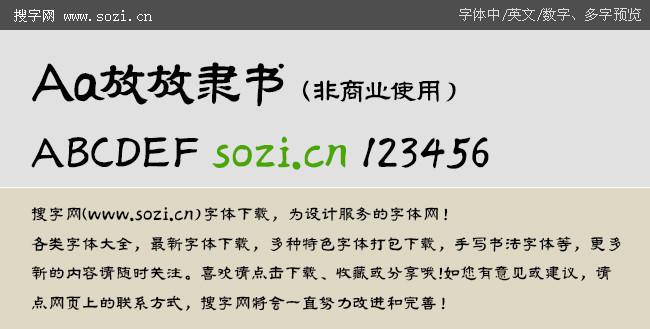
Aa放放隸書(非商業(yè)使用)
搜字網(wǎng)給大家提供一款A(yù)a放放隸書(非商業(yè)使用)中文字體下載,該字體筆觸較為粗實,字體清晰明朗,端莊大氣,具有很好的視覺效果,適合包裝畫冊等兒童卡通宣傳廣告等應(yīng)用(此字體為個人非商用版,商用可以聯(lián)系QQ:1006760504)。